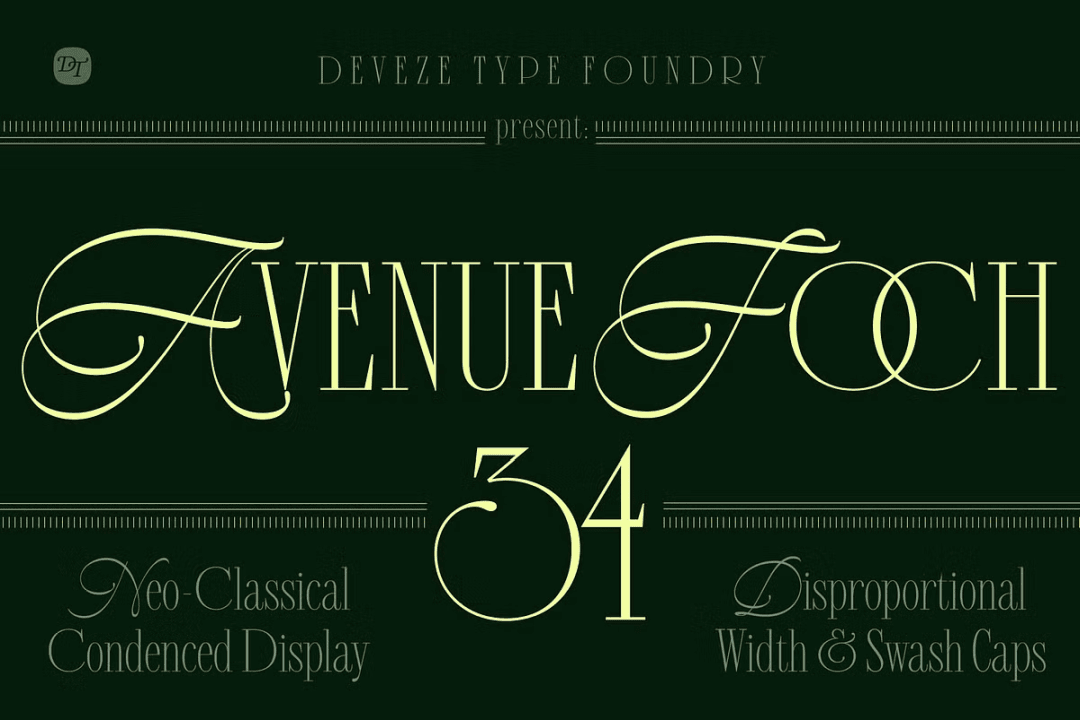
DT Avenue Foch
最近流行も落ち着いてきたスクリプトとコンデンスなモダンローマンのコンバインド。この手の多くはスクリプトがカッパープレートで、こちらも一見そうは見えるが、実はかなり細めのイタリックとなっている。またローマンの方も通常はない小文字があり、大文字がスクリプト+モダンローマン大文字の Majuscule、大文字がスクリプト+モダンローマン小文字の Miniscule と、スクリプトなしのただのモダンローマンの Regular があって、使い分けができるようになっているのも便利である。